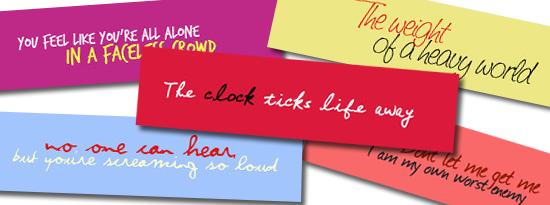
Más de 60 tipografÃas de escritura manuscritaCategorÃas: TipografÃa Como buen aficionado a la tipografÃa, ya son muchas las ocasiones en que he dejado constancia en el blog Cosas Sencillas, dejando una buena ración de información sobre las tipografÃas manuscritas, y cosas realacionadas. Es necesario resaltar que el emplear tipos de letras en el texto escritas a mano llama la atención de la mayorÃa , a pesar de que se presenta en una pantalla de ordenador. Los tipos de letras que simulan la escritura a mano puede ser muy útil para lograr ciertos objetivos de diseño, pero no se pueden aplicar en cualquier caso. El texto largo y difÃcil de leer es un ejemplos en los que los tipos de letras de escritura a mano puede ser doloroso para el lector. Pero para los encabezados y notas breves escritos a mano las fuentes pueden ser muy útiles. Asà que si estás cansado de los bloques con diseño de tipos de letras Serifs que dan un aspecto un tanto serio, te gustará darle un vistazo al artÃculo 60+ Handwriting Fonts Cool Collection, de Best-Photoshop, en donde nos proporcionan algunos tipos de letras de estilo manuscrita o escritura realizada a mano para que podamos agregar algunos toque humano a tu diseño y que este sea menos formal. En dicho artÃculo podemos ver una vista previs de los tipos de letras y el enlace a su descarga. Es cierto que existe muchos tipos de letras con estilo de escritura a mano por ahÃ, pero espero que esta recopilación serÃa suficiente para empezar. de ese modo podemos encontrar algo que se ajuste a tu diseño, según tu de estado de ánimo... si estás romántico, melancólico, lúdico o loco. Tu eres el que decide que aspecto quieres trasmitir... después de todo, el diseño se supone que debe ser un derecho subjetivo. Publicado el 06/07/2009 por Toni